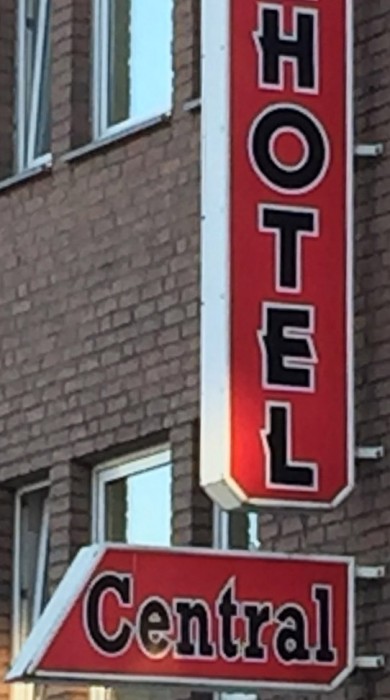
Fontname gesucht...
also bei der Schrift komme ich sofort auf einen Gedanken: Dynamo, auch wenn es die Dynamo definitiv nicht ist. Die Dynamo ist ein uralter Mottenfiffi und sollte eigentlich jedem bekannt sein. Man sieht sie immer wieder mal auftauchen, auch dann wenn man sie am wenigsten erwartet.
Dynamo
Originally designed by K. Sommer for Ludwig & Mayer in 1930.
Designer: K. Sommer
Year: 1930
Von da an geht es sofort auf Identifont.com und in die Suche nach ähnlichen Schriften zur Dynamo. Es sollte dabei aber auch in Betracht gezogen werden, dass es sich um Handarbeit handeln könnte. Und da hätte ich auf die Schnelle als Anregung für das Konstruktionsprinzip folgendes zu bieten:
Warlock Heavy
Year: 1995
Warlock Ultra Heavy
Year: 1995
Mein Vorschlag wäre also eine ggf modifizierte Warlock Ultraheavy oder was sehr ähnliches ... Allerdings bringt mich Identifont da nicht an weitere Alternativen zur Warlock heran. Ggf. könnte der Frager sich ja mal von einem Fontanbieter eine Rastergrafik mit dem Wort HOTEL in der Warlock herunterladen und dies einer Schriftensuchmaschine zum Fraß vorwerfen? Unmodifiziert habe ich das gerade gemacht ...
Ich vermute daher Handarbeit in Anlehnung an die oben gezeigten Schriften. Das sieht für mich sehr plausibel aus. Basis war dann eine geometrische Grotesk. Probiere mal den Umbau einer Futura ExtraBlack?